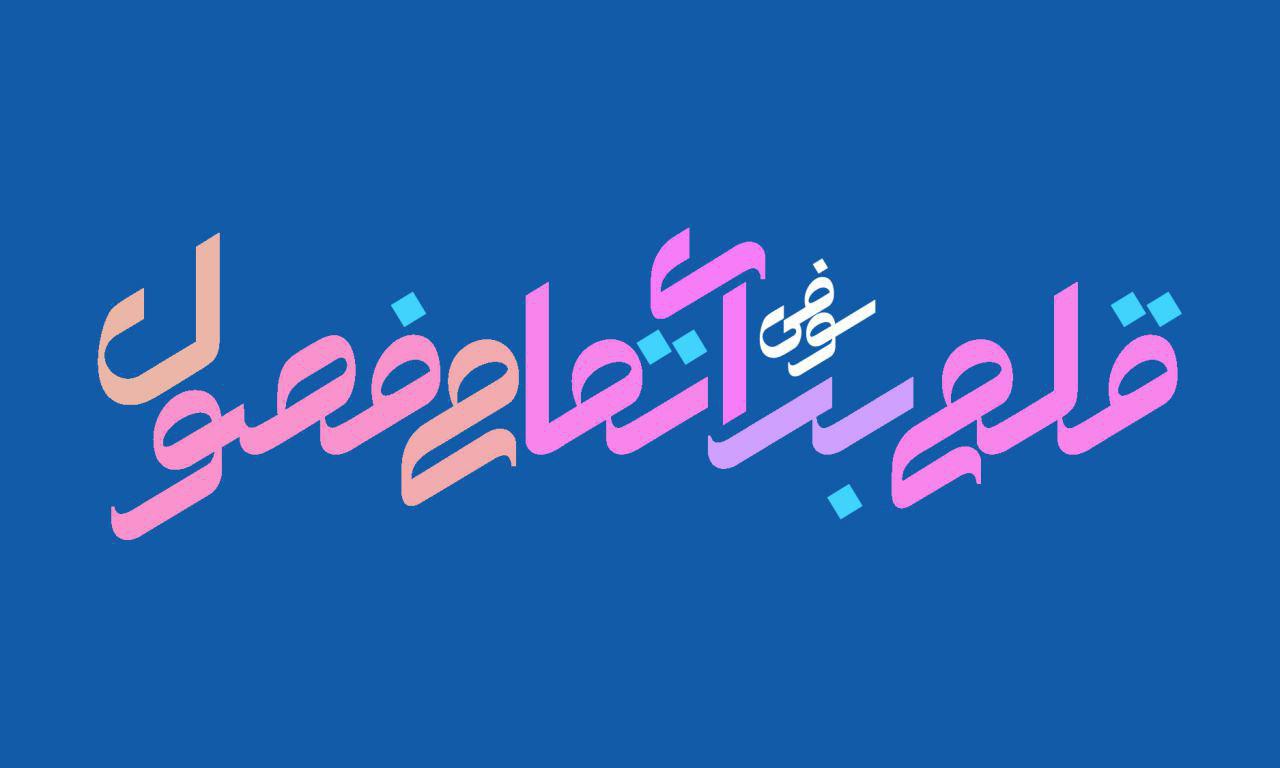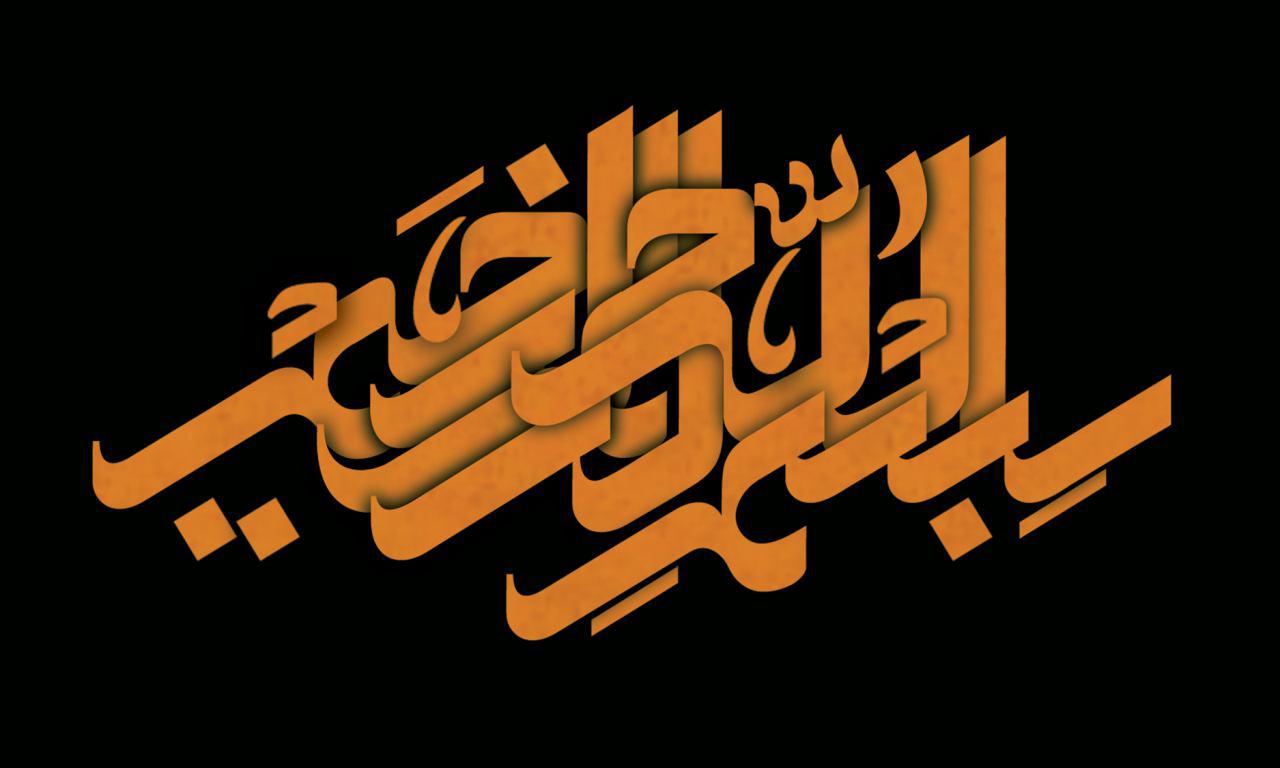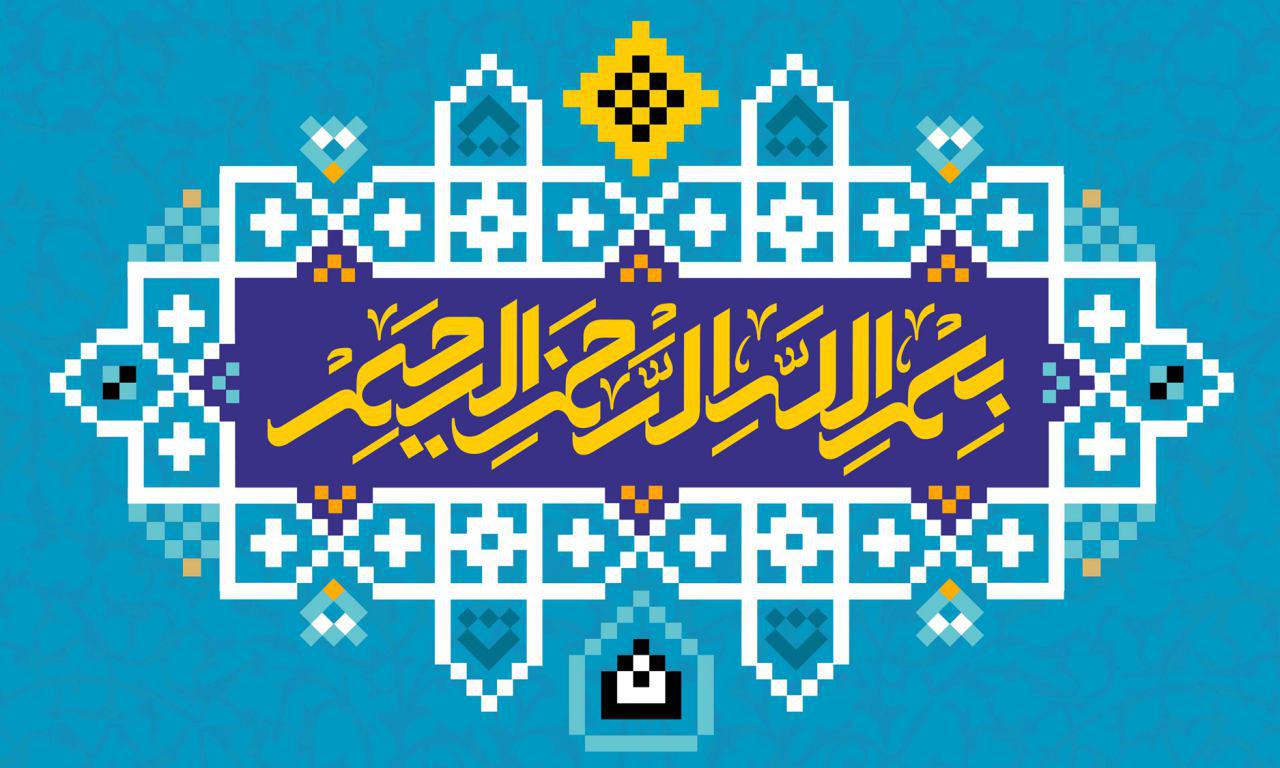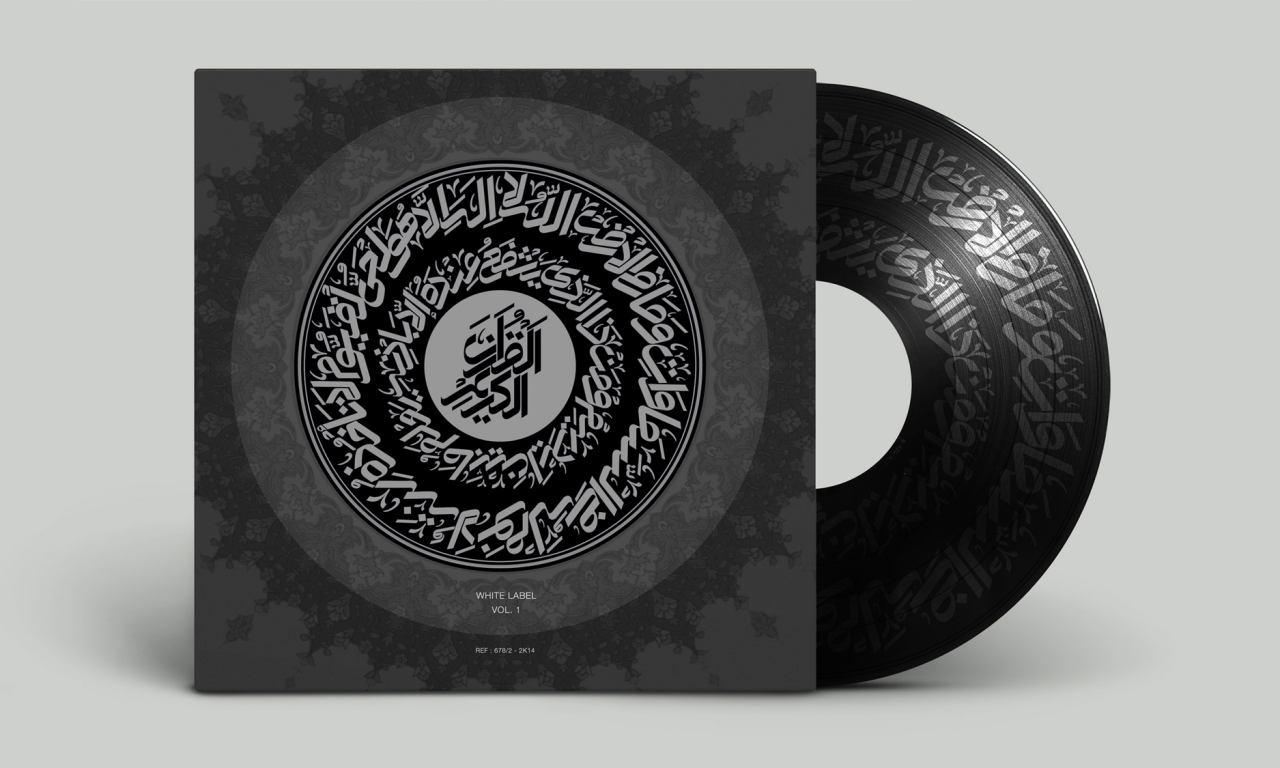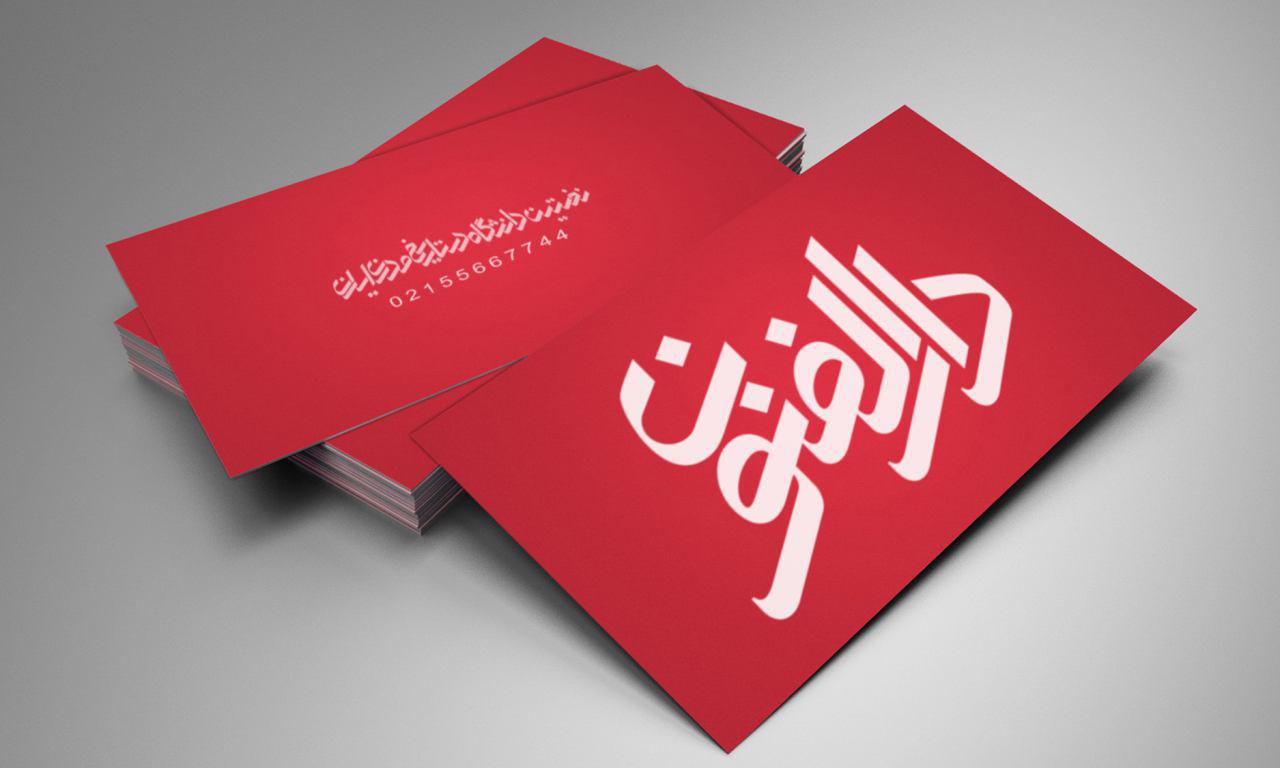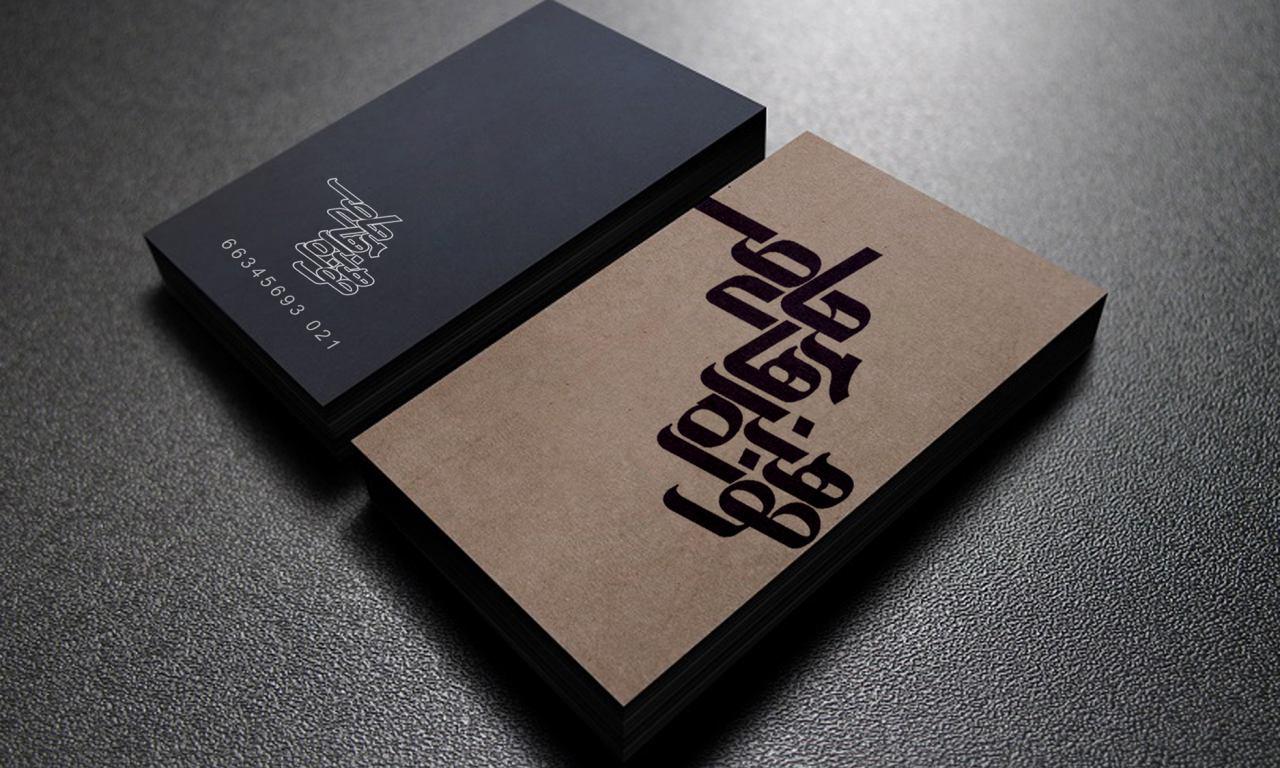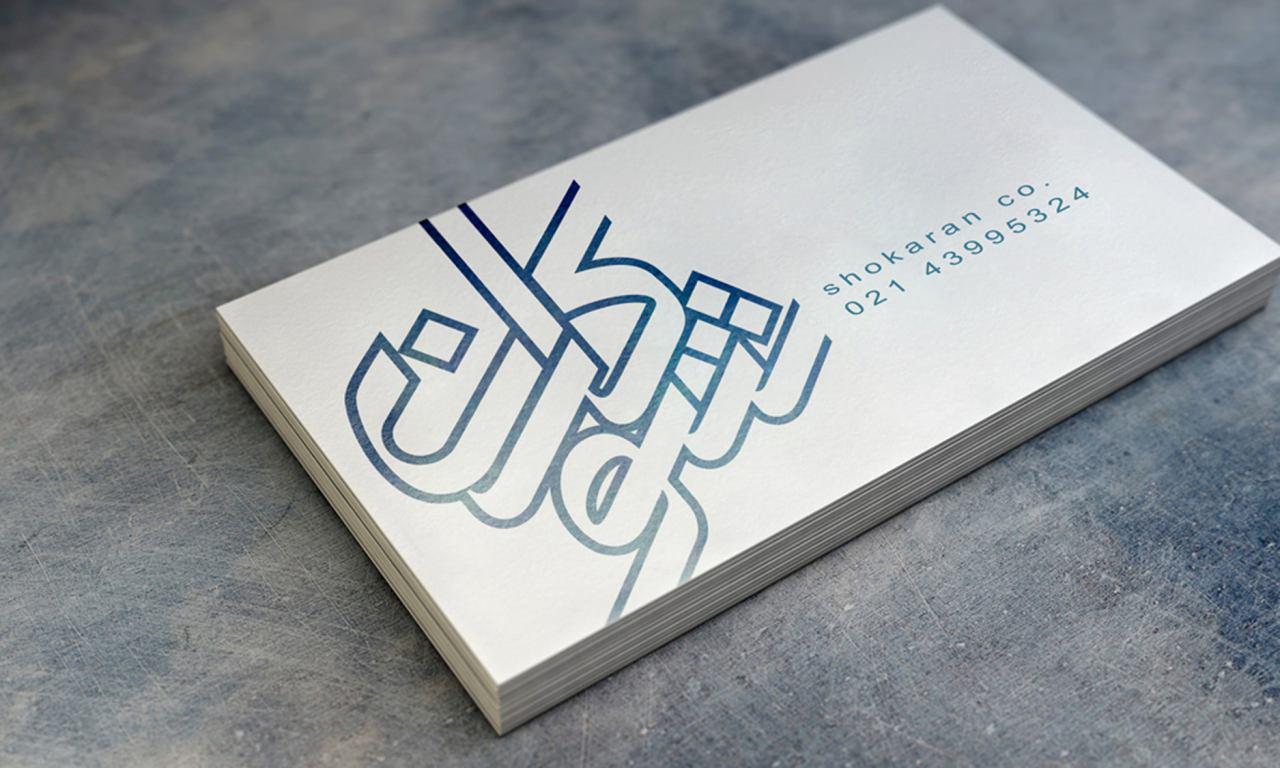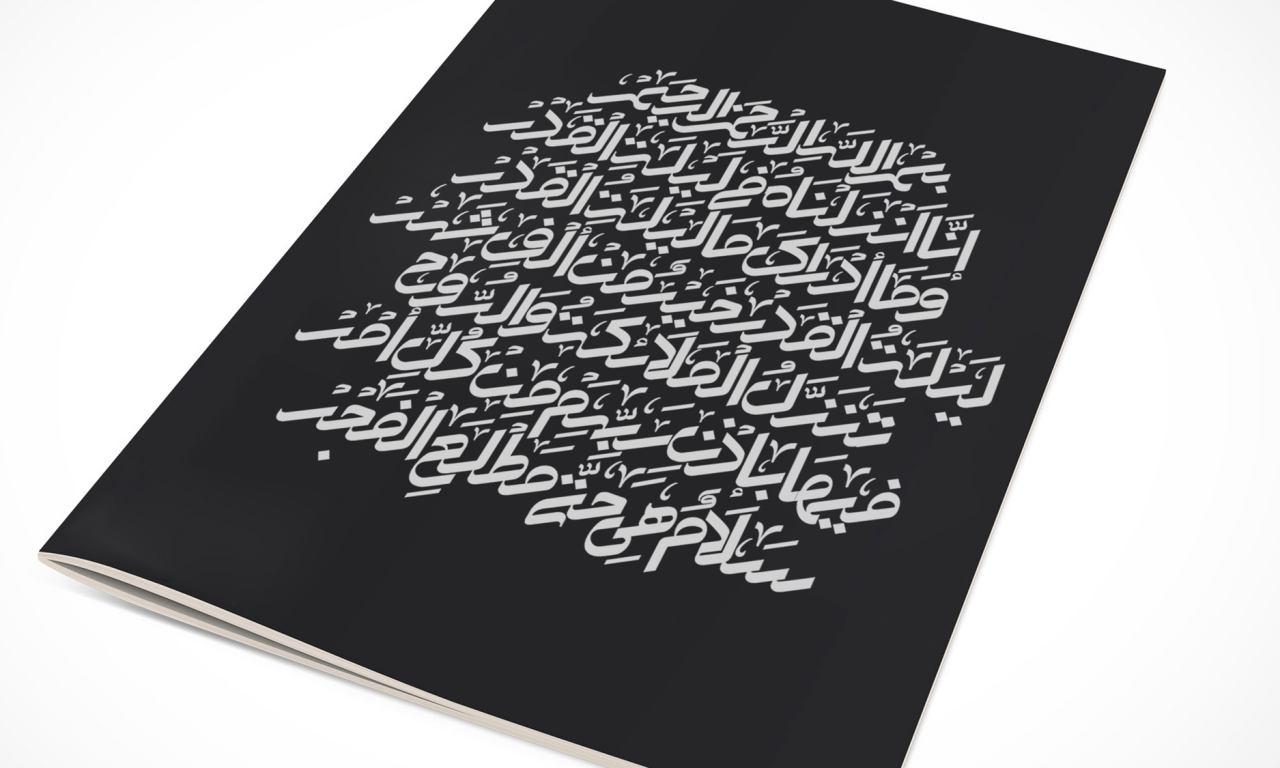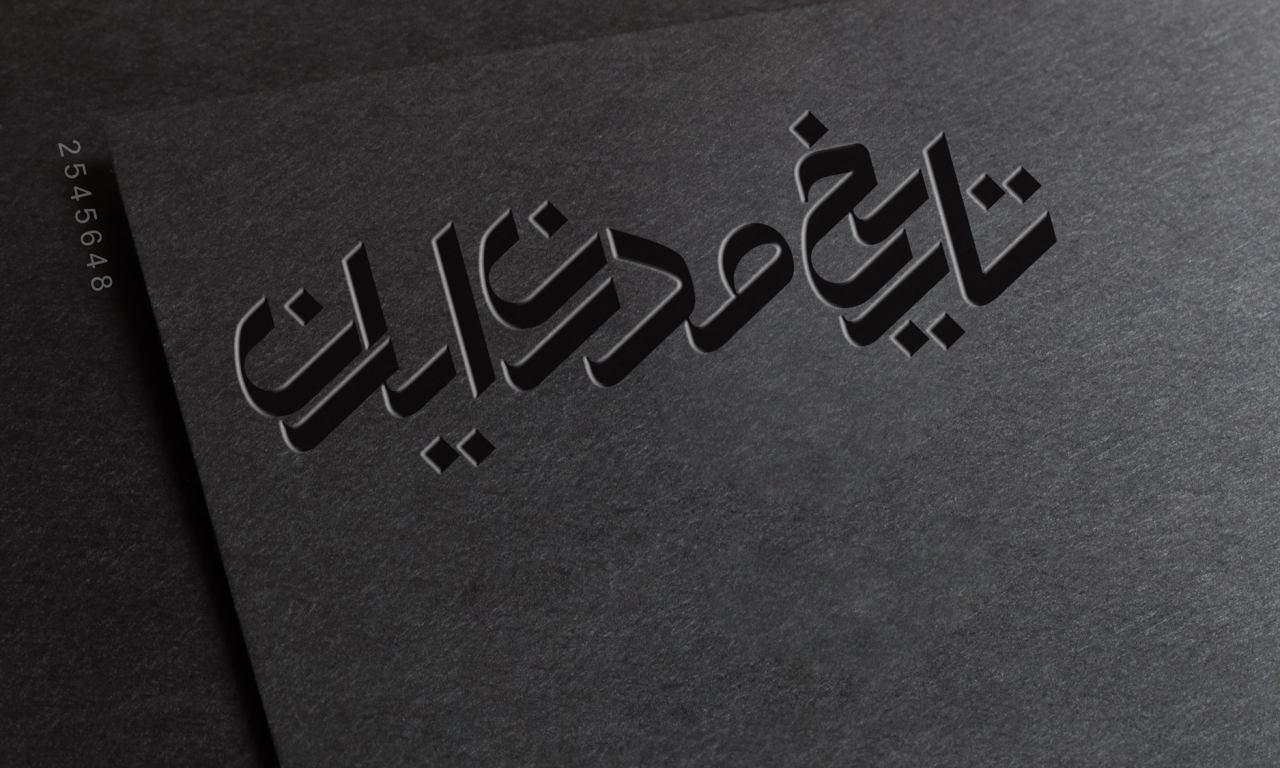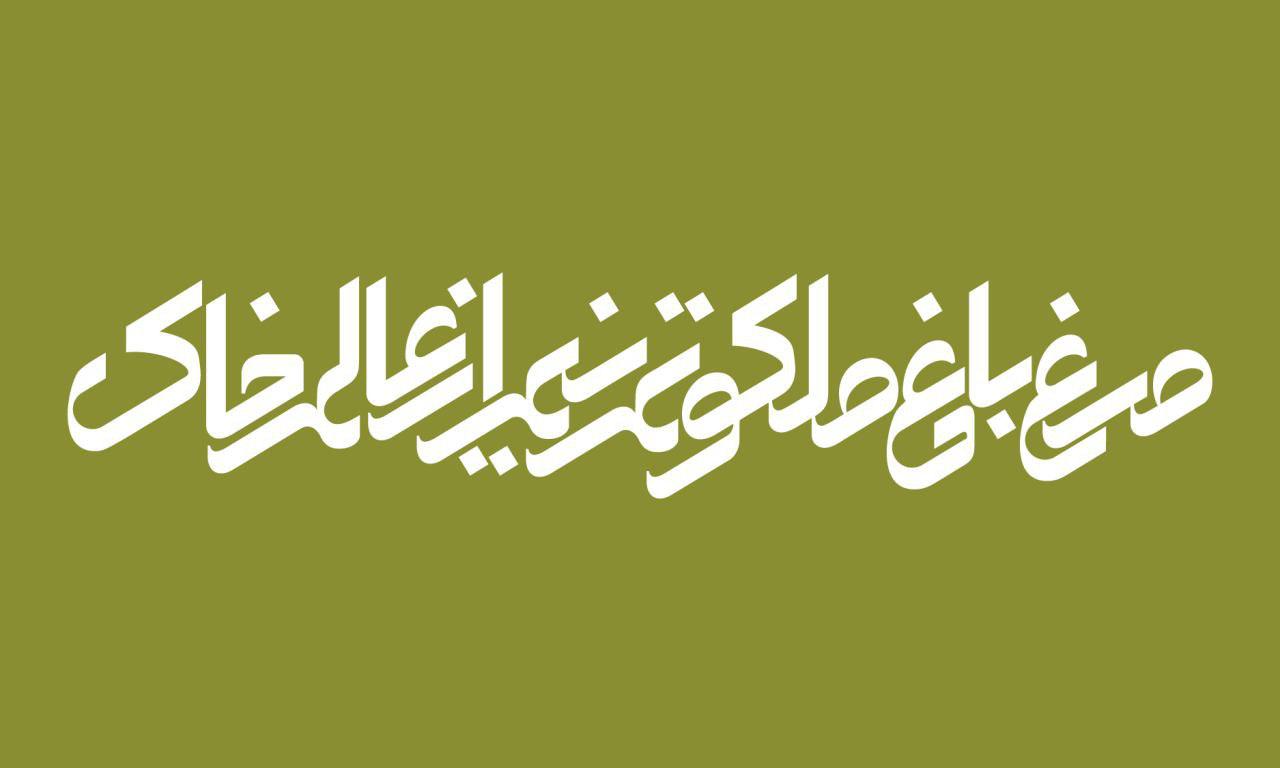
w_Soofee
درباره قلم سوفی
ساختار اصلی قلم سوفی بر اساس خط ثلث ایجاد شده است. خطی که به زیباترین حالت می تواند وامدار حرکتی نوین در عرصه ی گرافیک و تایپوگرافی کشور باشد. تعداد بسیاری از طراحان خلاق گرافیک در ایران و کشورهایی با پایه ی خط ایرانی و عربی درطی این سالها به نحوی در گسترش خط ثلث سهیم بوده اند. اما آیا به همان اندازه که خط ثلث جایگاه خود را در گرافیک مدرن امروزی یافته، توانسته ماهیتی نو در ساختار اصلی خود ایجاد کند؟ ماهیتی که این خط را منحصرا به گرافیک و ریشه های اصلی آن مربوط سازد؟
قلم سوفی را می توان حاصل دخالت گرافیک در خط نویسی و خطاطی کهن این مرزو بوم دانست. این قلم با ریتمی که بر اثر تکرار ضربه های مایل و بلند ایجاد نموده القاء کننده ی نظم، زیبایی وهمچنین انرژی و حرکت در یک اثر تایپوگرافی می باشد. اصلاح دوایر و طراحی خاص تزئینات و اعراب این قلم به برقراری نسبت میان سفیدی و سیاهی داخل و خارج حروف کمک به سزایی نموده است. نسبت کمترین و بیشترین ضخامت حرکت در این قلم یک به دو می باشد. به منظور داشتن یک کرنینگ مناسب، نوع دیزاین کاراکترها و ارتباط فرمی آنها با هم ارتباط مستقیم دارد. به این نحو که هرحرف و یا نهایتا کلمات در کنار هم مثل یک پازل به درستی قرار گرفته و ارتباط مناسبی از نظر بصری با یکدیگر پیدا می کنند. در طراحی کارکترها به منظور زیباتر و خواناترنمودن این قلم ، به صورت جداگانه انتخاب های دیگری نیز برای کاربران قرار داده شده است. نوع طراحی این قلم به نوعی است که می توان از آن در پروژه های بسیاری استفاده نمود و این تنها به خلاقیت طراح در استفاده ازین قلم بستگی دارد.
آیدین وفاداری
آیدین محمد وفاداری | متولد ۱۳۵۹ تهران | کارشناسی ارتباط تصویری از دانشکده هنرهای زیبای دانشگاه تهران | کارشناسی ارشد گرافیک دانشکده هنردانشگاه آزاد تهران | همکاری با شرکتها و آژانسهای تبلیغاتی در زمینه طراحی گرافیک | افتخار همکاری و شاگردی استاد بیژن جناب در استدیو جناب | افتخار شاگردی در محضر استاد صداقت جباری و استاد احصایی | مدرس تایپوگرافی و طراحی حروف فارسی | شرکت و برگذاری نمایشگاه های گروهی در زمینه گرافیک و تایپوگرافی درداخل و خارج از کشور